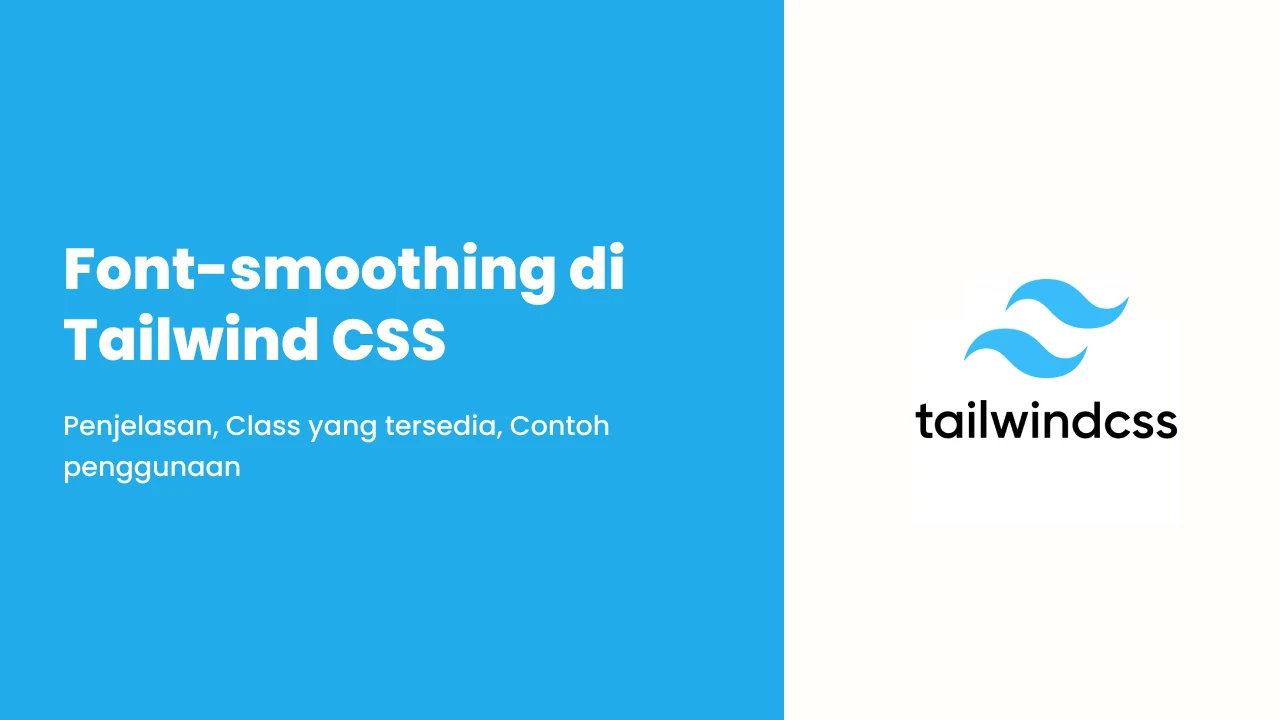
Apa itu font-smoothing?
font-smoothing adalah cara untuk membuat teks di layar terlihat lebih halus dan enak dibaca. Tailwind CSS menyediakan class khusus supaya kita gampang mengatur hal ini.
Class yang tersedia:
antialiased
➔ Membuat teks dirender dengan efek grayscale smoothing, sehingga teks terlihat lebih halus dan sedikit "abu-abu".
➔ CSS yang dijalankan:
-webkit-font-smoothing: antialiased;
-moz-osx-font-smoothing: grayscale;
subpixel-antialiased
➔ Membuat teks dirender dengan subpixel smoothing, lebih tajam di beberapa layar.
➔ CSS yang dijalankan:
-webkit-font-smoothing: auto;
-moz-osx-font-smoothing: auto;
Contoh penggunaan:
1. Membuat teks lebih halus dengan antialiased:
➔ Teks akan lebih soft dan halus.
2. Membuat teks lebih tajam dengan subpixel-antialiased:
➔ Teks akan terlihat lebih detail dan tajam.
Responsive Design:
Kalau mau efek font-smoothing berubah di ukuran layar tertentu (misal berubah saat layar besar), kamu bisa pakai breakpoint seperti ini:
➔ Di layar kecil teks akan halus (antialiased), dan saat layar besar (medium screen) akan tajam (subpixel-antialiased).